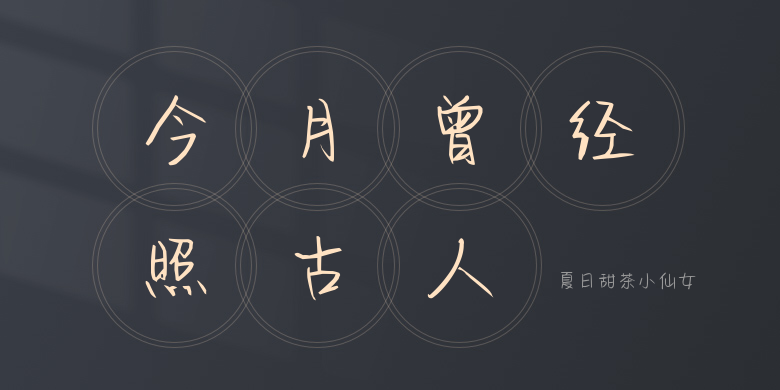
夏日甜茶小仙女
夏日甜茶小仙女,这款字体结构工整、笔画清晰,兼顾美观与易读性,适用于标题、正文、海报、包装、LOGO 等多种场景。字形优雅稳定,风格百搭耐看,适配日常排版与创意设计,让文字呈现更舒适、更具质感。夏日甜茶小仙女一笔一画,皆是细节,以均衡的比例、流畅的线条打造舒适视觉体验,字形端正大气,风格简约现代。无论是商业设计、品牌宣传还是日常排版,都能轻松驾驭,让文字更有格调与力量。夏日甜茶小仙女字体下载。